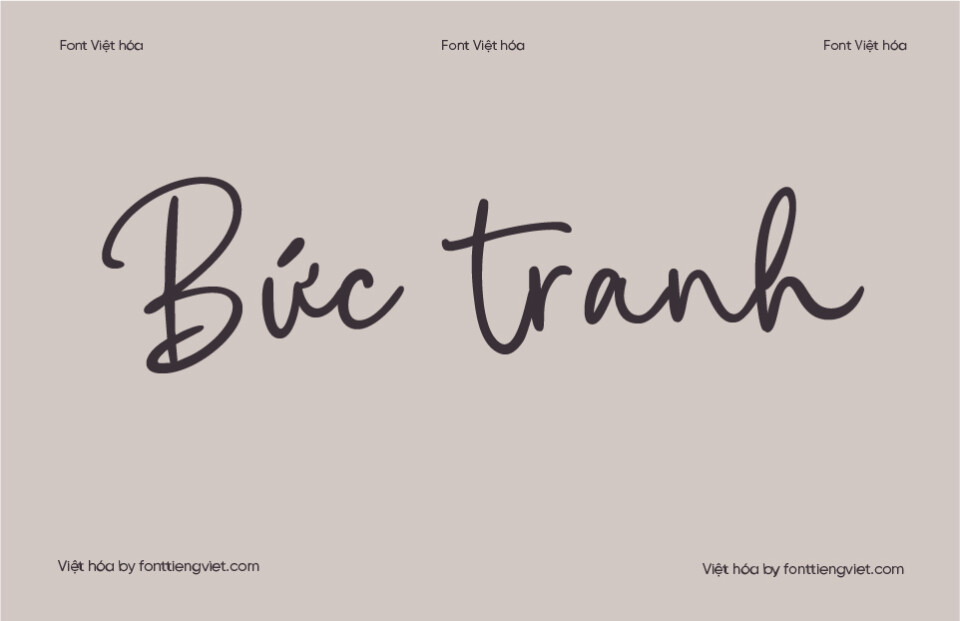
Giới thiệu về Font Việt hóa 1FTV VIP Ringchest
Trong thế giới đồ họa hiện đại, việc lựa chọn Font Chữ phù hợp đóng vai trò then chốt để tạo nên sự khác biệt. Font Việt hóa 1FTV VIP Ringchest là một trong những bộ font mang phong cách cổ điển nhưng không kém phần sang trọng. Với các đường nét uốn lượn tinh tế, bộ font này giúp người dùng dễ dàng truyền tải thông điệp một cách chuyên nghiệp. Đặc biệt, phiên bản này đã được tối ưu hóa tiếng Việt hoàn chỉnh, giúp các bạn học sinh và giáo viên sử dụng thuận tiện trong các bài thuyết trình hay tài liệu học tập mà không lo lỗi font.
Ưu điểm nổi bật của Font Việt hóa 1FTV VIP Ringchest
Thiết kế sáng tạo và đa dụng
Font Việt hóa 1FTV VIP Ringchest sở hữu cấu trúc ký tự độc đáo với những đường bo tròn mềm mại. Đây là lựa chọn lý tưởng cho các dự án thiết kế thiệp mời, bìa sách hoặc trang trí báo tường tại trường học. Sự cân bằng giữa nét thanh và nét đậm tạo nên một tổng thể hài hòa, giúp văn bản trở nên dễ đọc và thu hút ánh nhìn ngay từ lần đầu tiên.
Kết luận về bộ font ấn tượng
Việc sử dụng Font Việt hóa 1FTV VIP Ringchest không chỉ nâng cao thẩm mỹ cho sản phẩm mà còn thể hiện sự chỉn chu trong công việc. Nếu bạn đang tìm kiếm một giải pháp làm mới phong cách thiết kế của mình, hãy trải nghiệm ngay bộ Font Miễn Phí, Font Việt Hóa, Font Việt hóa 1FTV VIP Ringchest chất lượng này. Chắc chắn sự độc đáo của nó sẽ mang lại những cảm hứng sáng tạo tuyệt vời cho cộng đồng yêu thích nghệ thuật chữ viết.